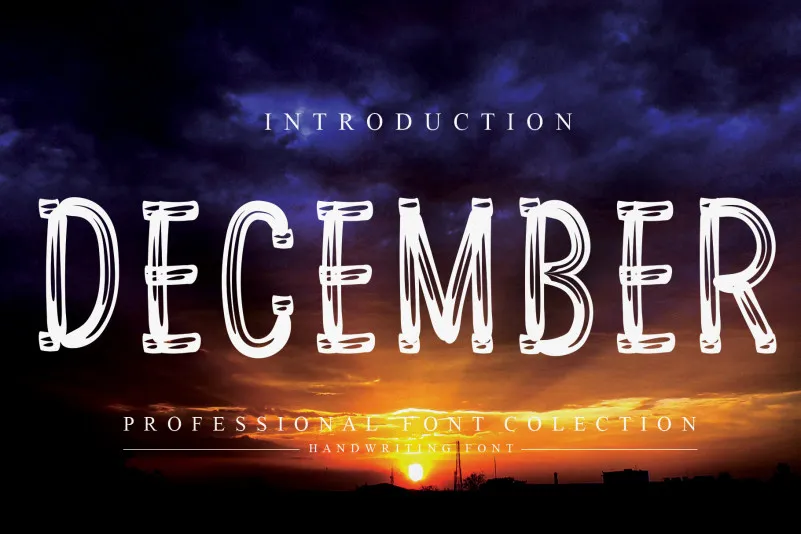
December Display Font – Download Grátis
A fonte “December Display Font”, criada pelo designer andikastudio, é uma tipografia com traços grossos projetada para usar em letras grandes e chamativas. Esta criação brushy não apenas adiciona um toque especial às suas ideas criativas, mas também faz delas realmente viverem. Com linhas fortes e estilizadas, essa fonte brincalhona é perfeita para destacar seus projetos de design em eventos noturnos ou mesmo durante a temporada do Natal. É uma ótima opção para aqueles que buscam um visual vibrante em letras grandes e desejam dar um toque especial ao seu material gráfico.